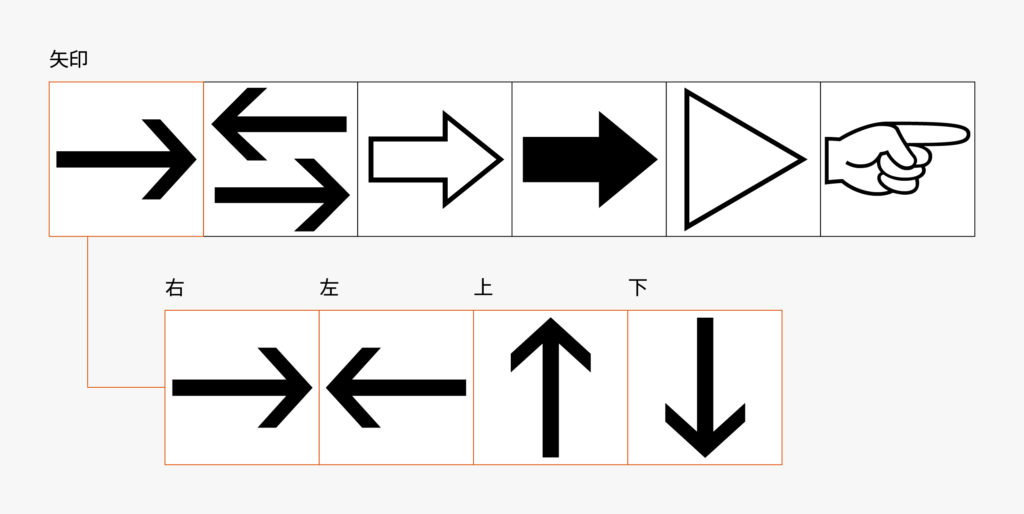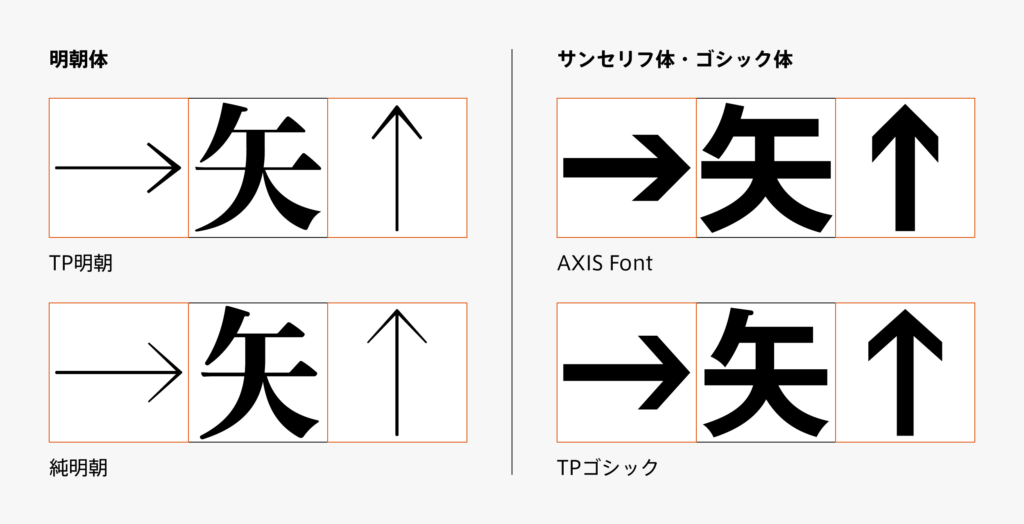
和文約物04「矢印」
前回の括弧と同じく、矢印にもいくつか種類があります。そして矢印によっては上下左右でそれぞれグリフを用意するのも忘れずに。横向きと縦向きとで同じカタチを使っても同じような太さに見えないことがあり、その場合は見た感じで同じくらいに見えるよう調整を入れます。どこで同じカタチを使ったか、どこに調整を入れたか、きちんとチェックしながら進めないと修正があった際に困ってしまいます。
矢印は明朝体とゴシック体・サンセリフ体で太さの付け方が変わるのもポイントです。ゴシック体・サンセリフ体は他のグリフと同じような太さにします。対して明朝体は太いウエイトでも細めの矢印が一般的で、漢字の横画に近い細さになっています。縦向きの矢印なら縦画のような太さにする、なんてことはしないようです。